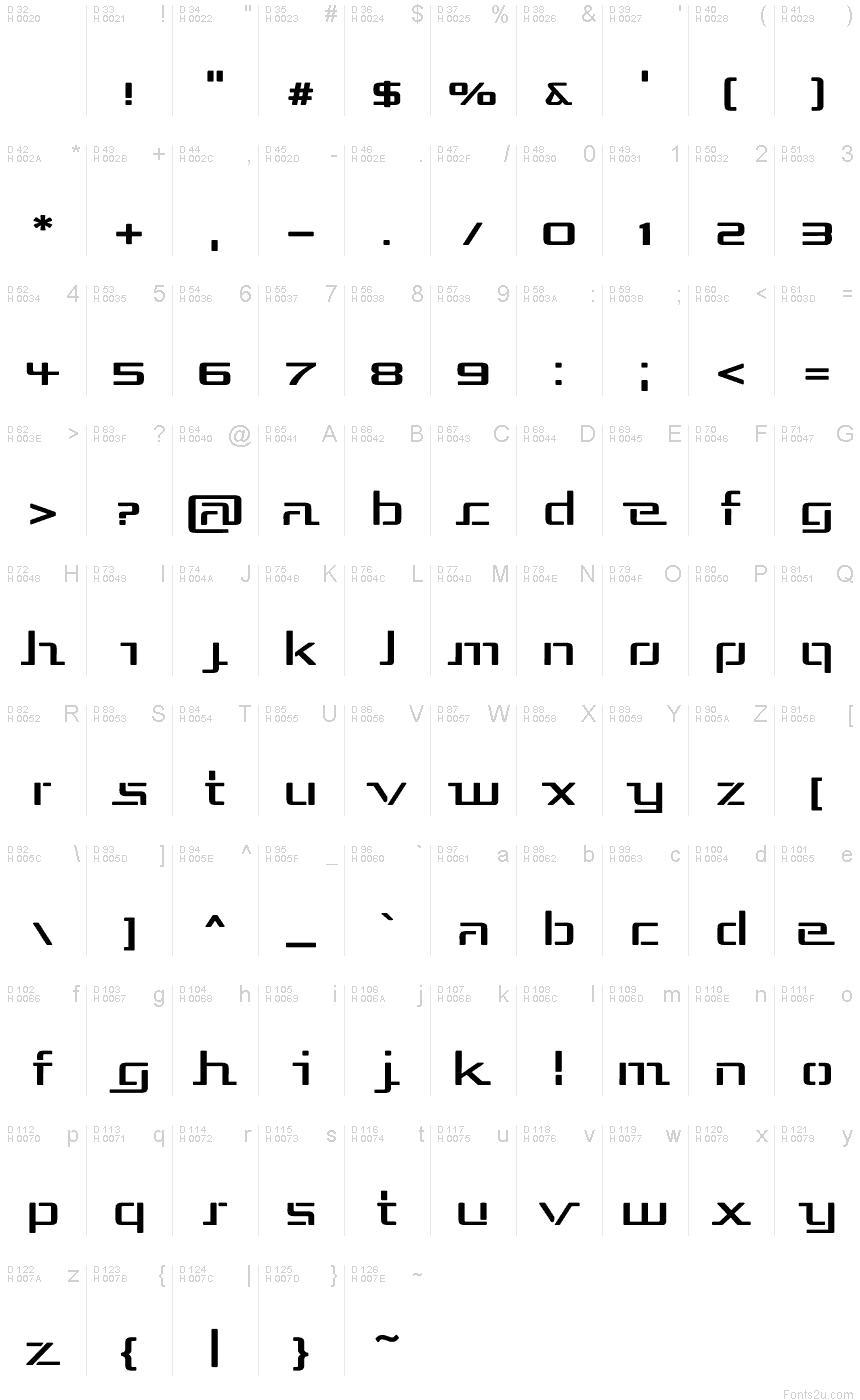
Republika III Exp
Republika III Exp di Apostrophe è un font display futuristico e gratuito, costruito su moduli spessi e arrotondati che sembrano provenire direttamente da un alfabeto retro-tech. Le lettere poggiano su curve quadrate, aperture nette e alcuni decisi tratti verticali, donando all'intero design un ritmo elettronico fluido, che appare più progettato che scritto.
È la scelta naturale per locandine sci-fi, loghi di giochi, copertine di album, titoli e branding per progetti legati alla tecnologia musicale o alla cultura digitale. Essendo un font gratuito, dà il meglio di sé dove le lettere possono rimanere brevi e grafiche: le linee di copertina, i monogrammi e gli header d'impatto si adattano perfettamente alle sue forme compatte e quasi segnaletiche.